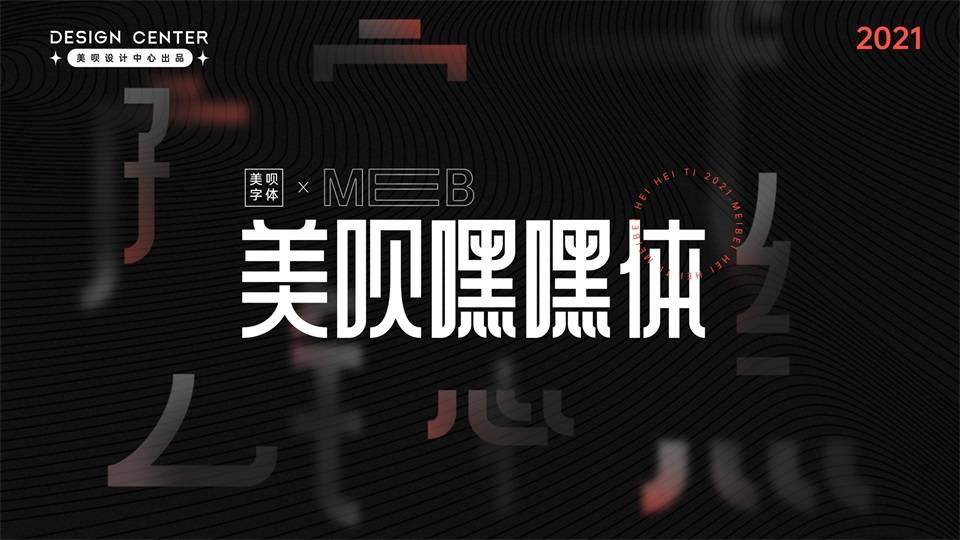
美呗嘿嘿体由美呗设计团队制作,该团队为了让品牌符号更加鲜明、让美呗er更有归属感,他们秉承着“开放、合作、创新“公司价值观推出的一款通用型强的黑体字体,有着时尚、年轻、女性化的气质。美呗嘿嘿体,允许任何个人和企业免费使用。
美美呗嘿嘿体适合字电商、海报设计等平面设计上使用,汉字字数:2500(用来创作海报的标题字,足够使用了。)